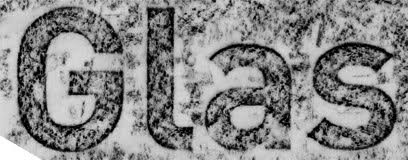
hat ähndlichkeiten mit Arial Narrow
Weiss jemand von euch den Namen dieser Schrift...ich komm einfach ned drauf. :(
na ja, is einfach die ähnlichste die mir eingefallen ist.
Leider liegen die beiden knapp daneben, es handelt sich nämlich um die FF DIN ;)
Man erkennt es daran, daß das »G« links keine Gerade sondern eine Kurve hat und das »s« in der Mitte schräger ist.
Spitze der Mann! Jens, auch am a ist ein deutlicher unterschied (Breite) und dann ist es auch der FF Din Bold. WOW. Arial? kenne ich gar nicht...